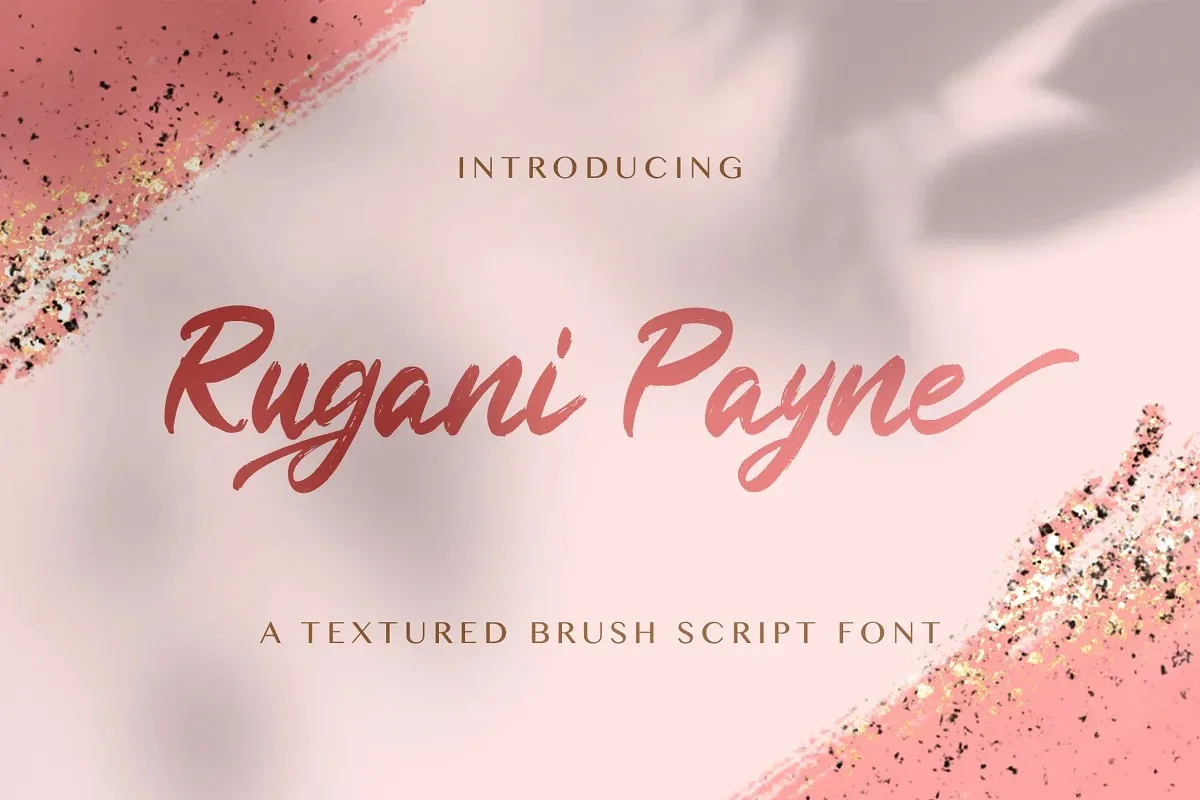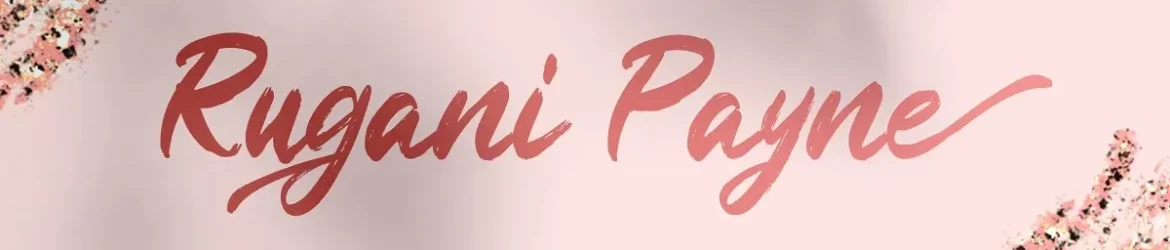
Rugani Payne Font – Download Grátis
Esta fonte script foi criada com o app Procreate, transmitindo uma arte livre e robusta. Suas ondas dramáticas tornam-a perfeita para diversos projetos criativos, como logotipos, cartões de convite ou impressão de frases motivacionais. Perfeita também para embalagens de produtos, cabeçalhos, identidades de marca, letras no cartão e até mesmo para rótulos. Seja você um designer gráfico que precisa de uma fonte elegante para seus projetos ou alguém apenas procurando por algo inovador, essa font é certamente a escolha ideal.